「大正ロマン」にぴったりな日本語フリーフォント
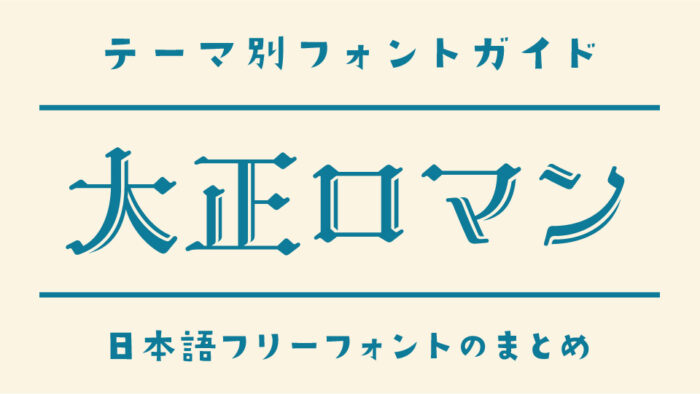
今回は、ハイカラな香りと懐かしさを感じる「大正ロマン」の世界観にぴったりな日本語フリーフォントをご紹介します。
大正ロマンといえば、和と洋が絶妙に溶け合ったモダンな文化、袴姿の乙女たち、ガス灯が灯る街並み、そしてどこか哀愁を帯びたレトロな空気が特徴的で、大正時代独特の文化や社会です。
そんな大正ロマンの世界観を彩るためにぴったりなフリーフォントをまとめてみました。
「大正ロマン」におすすめの日本語フリーフォント
あおさぎフォント
あおさぎフォントは、やわらかく親しみのあるレトロデザインが特徴の明朝体フォントです。どこか素朴でありながらも、レトロな洗練さを感じさせてくれます。乙女の日常や喫茶店のメニューなどにぴったりなフォントです。
晩秋レトロミン
晩秋レトロミンフォントは、クラシカルな明朝体をベースに、直線と円弧のラインで構成されたモダンな印象を加えたデザインフォントです。和洋折衷の大正文化を思わせる、落ち着きとおしゃれさが同居したデザインにぴったりです。
解星デコール
解星デコールフォントは、西洋のアール・デコ調の装飾な雰囲気をもつデザインフォントです。すらっと伸びる縦画や、独自の曲線が上品な大正ロマンなレトロ感にぴったりです。
ニューテゴミン
ニューテゴミンは、筆文字のニュアンスを取り入れた、しなやかな明朝体です。穏やかで流れるような筆致は、恋文や詩のようなやさしさを感じさせてくれます。女性的で繊細な印象にぴったりなフォントです。
セリフゴシック
セリフゴシックは、力強いゴシック体にセリフ(うろこ)がついた珍しいフォントです。大正ロマンのモダンで都会的なムードを演出できます。洗練された雰囲気に仕上げたいときにおすすめです。
大正略字
大正略字フォントは、大正時代に使われていた略字や活版をモチーフにしたフォントです。独特の骨格があり、活版印刷の風合いを感じさせてくれます。
ひな明朝
ひな明朝は、手書きのような温かみや、品のある表情を感じる明朝体です。かすれた筆使いが繊細で、文学少女や恋物語をテーマにしたデザインにおすすめです。
新レトロ丸ゴシック
新レトロ丸ゴシックは、どこか懐かしくやさしい印象を持つ丸ゴシック体です。丸みを帯びた形状が、大正時代のモダンと素朴さを同時に感じさせてくれます。レトロ喫茶や昭和ロマンの雰囲気を演出したいときにぴったりです。
しねきゃぷしょん
しねきゃぷしょんは、映画の字幕をイメージしてつくられたフォントです。柔らかなカーブと均整のとれた字形は、現代的なレトロさを演出してくれます。大正の街角で交わされるやさしい会話を想像させます。